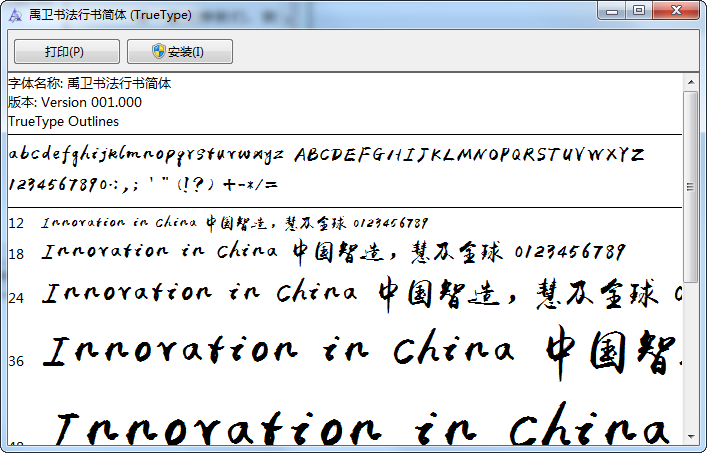
禹衛(wèi)書法行書簡體字體是一款風格獨特的毛筆行書字體,字體輪廓飄逸,俊秀美觀,運用于平面設(shè)計、名片設(shè)計、廣告創(chuàng)意等等領(lǐng)域,有需要這樣一份禹衛(wèi)書法行書簡體的朋友趕緊收藏吧。
禹衛(wèi)書法行書簡體是一款以毛筆行書書為主的GB_2312字庫,這里包含了常用字和生僻字共6763個,可廣泛適用于微軟office的各種軟件、qq、MSN等常用聊天工具、photoshop等主流繪圖軟件。